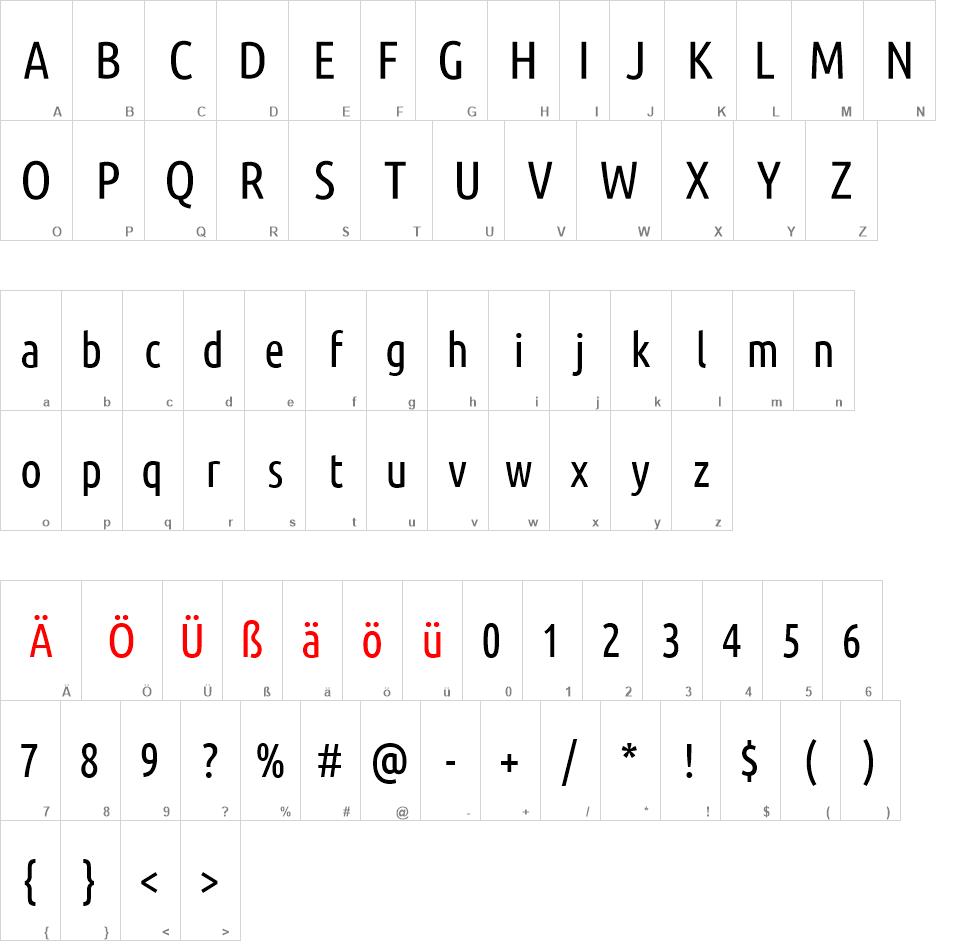
Ubuntu Condensed
Ubuntu Condensed font
Die Ubuntu-Schriftfamilie ist eine Gruppe von Sets, die zwischen 2010 und 2011 mit den neuen libre / open-Schriftarten übereinstimmen. Im Namen der Entwicklung, Canonical Ltd. Die breite Community für Freie Software wird vom Ubuntu-Projekt finanziert. Technische Studien zum Zeichensatzdesign und deren Implementierung werden von Dalton Maag durchgeführt.
Die neue Ubuntu-Schriftart wurde eingeführt, um die Ubuntu-Persönlichkeit sichtbar zu machen, und jedes Menü, jede Schaltfläche und jede Kommunikation wurde spürbar. Die Font Sans-Serif verwendet die Funktionen von OpenType und ist für die manuelle Anzeige auf Desktop- und mobilen Computerbildschirmen gedacht.
Der Umfang der Ubuntu-Schriftfamilie deckt alle Sprachen ab, die von verschiedenen Ubuntu-Benutzern weltweit verwendet werden, gemäß der Ubuntu-Philosophie, die besagt, dass jeder Benutzer seine Software in der von ihm gewählten Sprache verwenden kann. Das Ubuntu-Schriftfamilienprojekt wird daher um viele weitere Schriftsprachen erweitert.